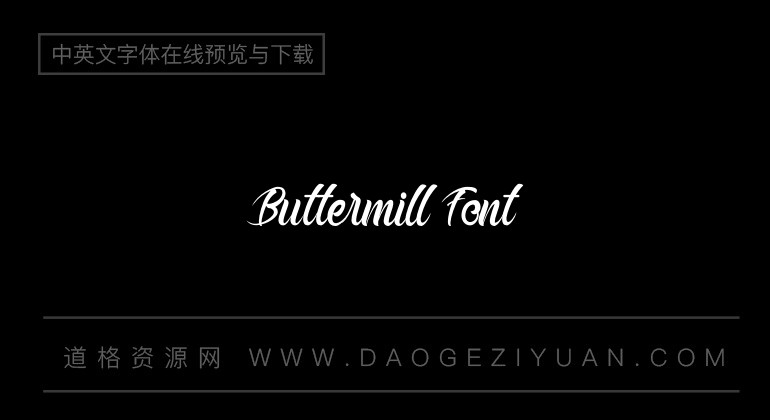
Buttermill Font 是一种优美的手写风格字体。它的笔画流畅,有一种非常自然的感觉,适合用于设计书籍、海报、标志、卡片等等。 Buttermill Font 有两种字重:常规和粗体。它包含大写和小写字母、数字、标点符号和特殊字符,支持多种语言。 Buttermill Font 的设计师是一位名叫 Jessica McCarty 的艺术家。她的字体设计风格以自然、轻松和愉悦为特点,很受设计师和艺术家的欢迎。内容介绍
Buttermill Font是一款非常不错的手写艺术字体,具有很好的视觉感,适合于文化类的宣传设计、商业类品牌的广告和产品包装设计以及个性化文字排版等较多场景。